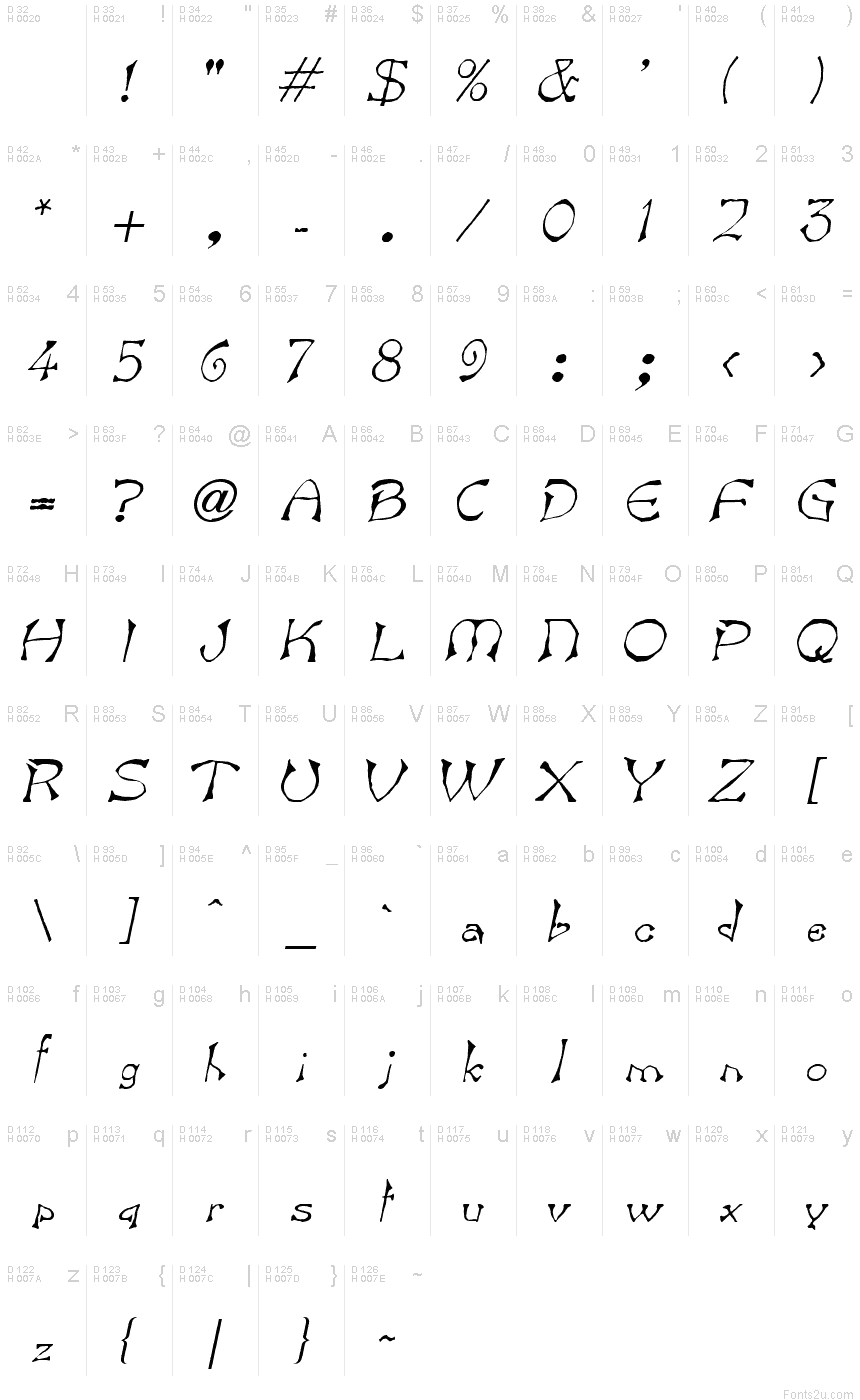
Bart Italic to darmowy, erodowany krój typu script o poszarpanych, nasyconych tuszem liniach, które wyglądają, jakby zostały szybko wydrapane na papierze. Pochylone kształty, nieregularne krawędzie i ostre zakończenia nadają rodzinie Bart niespokojną, odręczną energię, która natychmiast przyciąga wzrok, nie tracąc przy tym na czytelności.
Dzięki Bart Italic nadasz surowy, odręczny charakter plakatom, okładkom albumów, komiksom, zinom, planszom tytułowym, grafikom w stylu horroru czy tajemnicy oraz odważnym eksperymentom brandingowym. Ten darmowy font świetnie sprawdza się w większych rozmiarach, gdzie jego teksturalne detale mogą wybrzmieć; wypróbuj połączenie z czystym krojem bezszeryfowym w tekście głównym, aby zapewnić czytelność układu, pozwalając jednocześnie Bart Italic przejąć dramatyzm w nagłówkach i logotypach.